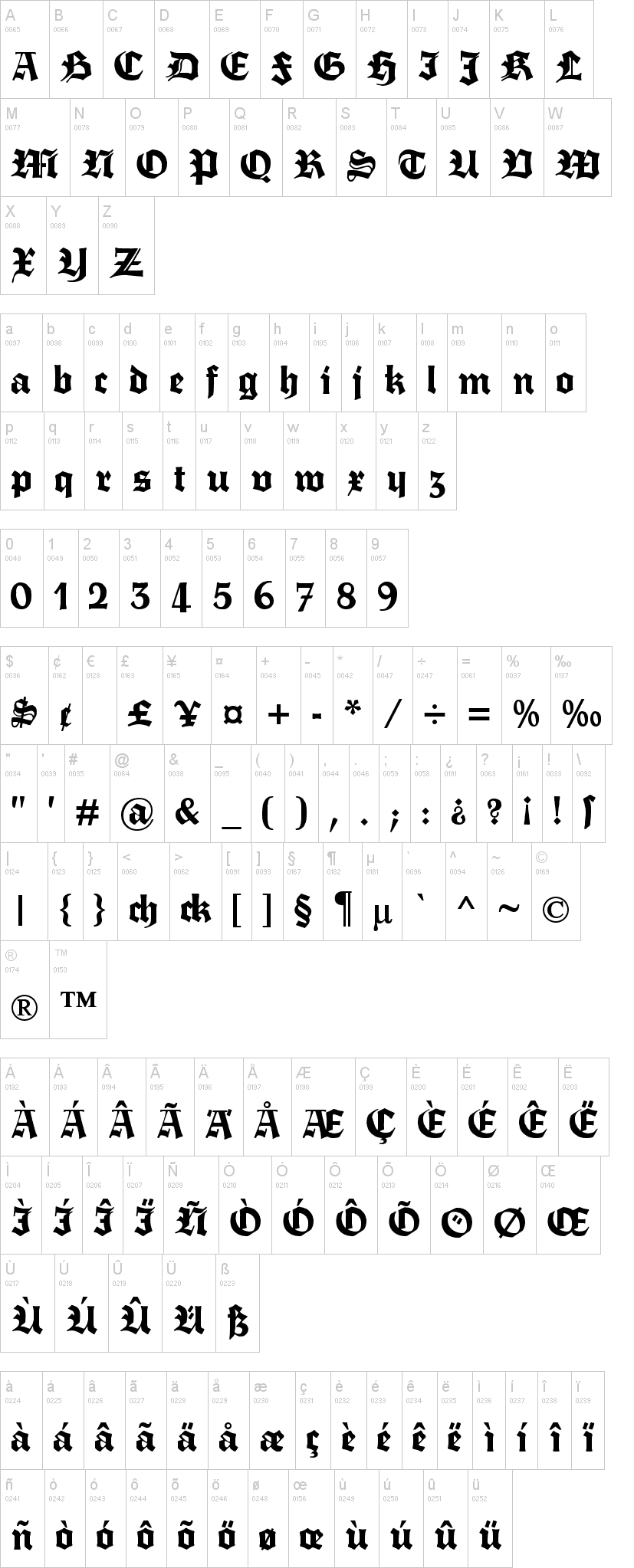
Fette Trump Deutsch是一款由德国设计师Hans-Jürgen Ellenberger设计的英文字体。它是一种“荷兰风格”字体,具有粗体、细体和明显的线条结构。它有着传统的英文字体风格,但又有着比较现代的特点。它的字母特点是大写字母有着非常明显的斜体,而小写字母则稍有缩写,更加有趣。Fette Trump Deutsch字体适用于任何类型的文字,尤其是在广告、标志和标签上有更好的效果。内容介绍
Fette Trump Deutsch是一款非常不错的手写艺术字体,具有很好的视觉感,适合于文化类的宣传设计、商业类品牌的广告和产品包装设计以及个性化文字排版等较多场景。